Tổng hợp 10 font chữ Happy Birthday đẹp, độc đáo và miễn phí giúp tiệc sinh nhật trở nên ấn tượng
Bạn đang muốn tạo một bữa tiệc sinh nhật ấn tượng, độc đáo và hoành tráng? Hay bạn muốn dành tặng người thân, người yêu lời chúc sinh nhật đặc biệt? Vậy đựng quên “gia vị” góp phần tạo nên sự ấn tượng đó là font chữ Happy Birthday đẹp nhé. Hãy cùng FPT Shop tìm hiểu các font chữ sinh nhật đẹp, miễn phí qua nội dung dưới đây.
Tổng hợp 10 font chữ Happy Birthday đẹp miễn phí
Cùng điểm qua 10 font chữ sinh nhật đẹp, miễn phí được FPT Shop tổng hợp dưới đây.
1. Font chữ Brusher
Đây là một font chữ viết tay mềm mại, kết hợp với các hiệu ứng cọ vẽ tạo cảm giác vui tươi và tự nhiên. Font được thiết kế đặc biệt cho các dịp sinh nhật như dùng để tạo băng rôn, trang trí trên các vật dụng cho bữa tiệc sinh nhật. Để sử dụng font chữ này bạn có thể dùng trực tiếp trên Canva.
2. Font chữ Dancing Script
Dancing Script tiếp tục là một font chữ viết tay hoàn hảo để bạn sử dụng trong bữa tiệc sinh nhật. Với thiết kế thanh lịch, mềm mại và đầy cảm xúc để tạo nên chữ Happy Birthday ấn tượng và đẹp mắt. Font chữ bao gồm đầy đủ bộ ký tự, hỗ trợ nhiều ngôn ngữ khác nhau.
3. Font chữ Grand Hotel
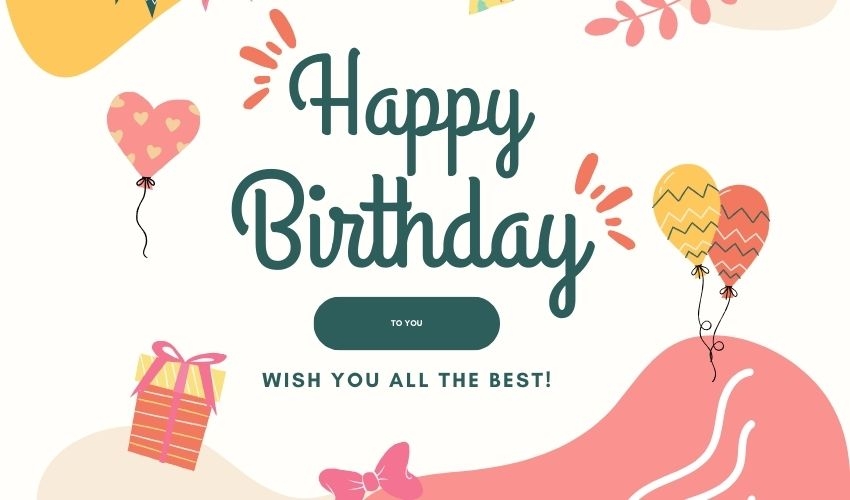
Với các nét vẽ cong nhẹ nhàng cùng các đường nét thanh mảnh, Grand Hotel là font chữ Happy Birthday đẹp mang đến cảm giác tinh tế cho người nhìn. Ngoài việc sử dụng để trang trí trong tiệc sinh nhật, font chữ Gramd Hotel còn được ứng dụng cho nhiều mục đích khác nhau như thiết kế thiệp mời, thiết kế logo, bao bì và website.
4. Font chữ Amsterdam One
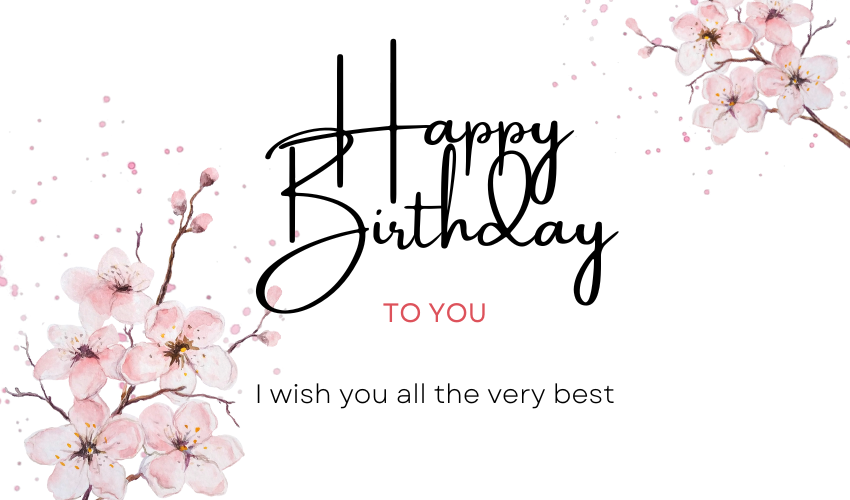
Amsterdam One là font chữ San-Serif đẹp, nổi bật với phong cách hiện đại, sang trọng và đậm chất nghệ thuật. Font chữ có nét cong nhẹ nhàng và các chi tiết tối giản giúp bạn tạo nên các văn bản cuốn hút và độc đáo. Font chữ có phiên bản Regular và Italic để người dùng lựa chọn phù hợp với ấn phẩm thiết kế.
5. Font chữ Halimum
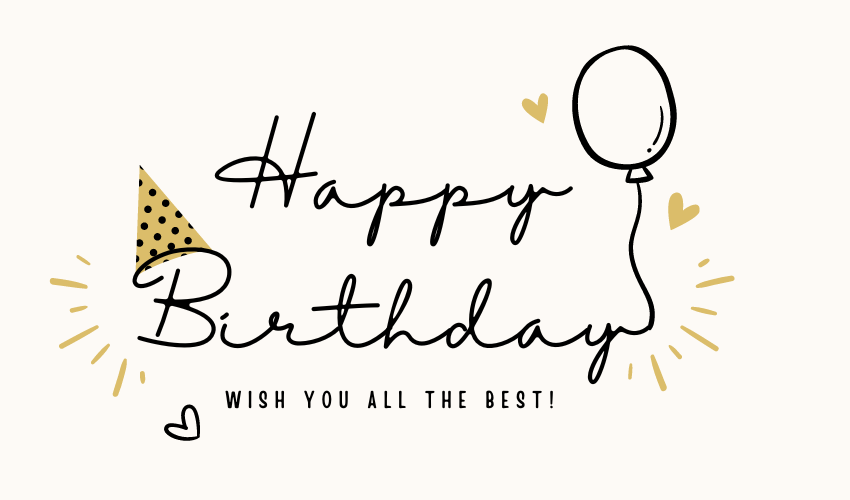
Halimum là font chữ cách điệu rất phù hợp trong thiết kế banner, thiệp mời, sản phẩm thời trang, đặc biệt là trong trang trí tiệc sinh nhật. Font chữ mang đến sự cân bằng giữa các nét thanh mảnh, nhẹ nhàng và liền mạch tạo cảm giác trẻ trung, thể hiện tính thẩm mỹ cao.
6. Font chữ More Sugar
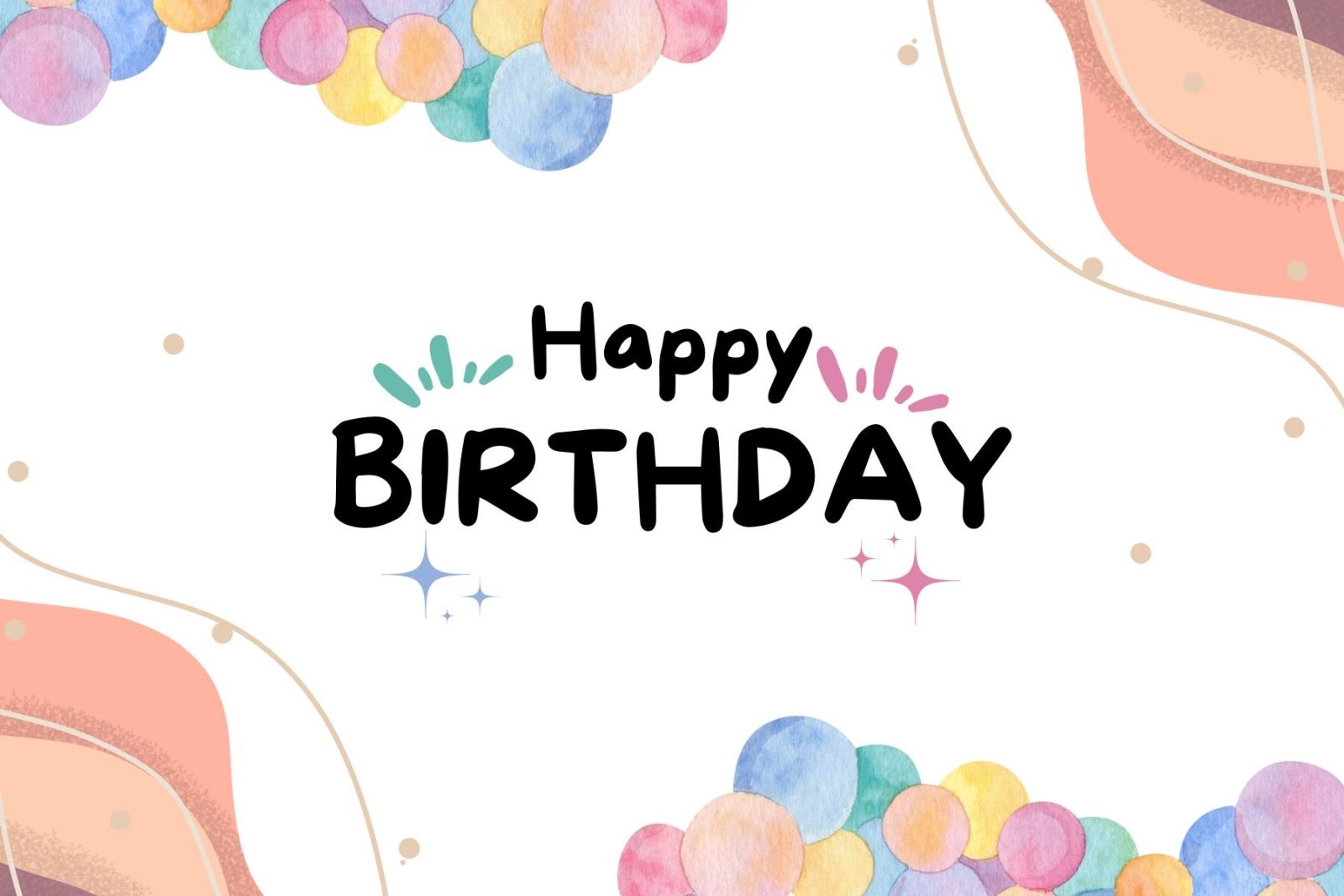
More Sugar là font chữ viết tay kết hợp giữa sự sáng tạo và tối giản. Font chữ có nét viết tự nhiên, đường nét uyển chuyển mềm mại tạo ấn tượng thị giác cho người nhìn. Bộ font More Sugar bao gồm các biến thể khác nhau như Regular, Thin và Extras giúp bạn tạo nên nhiều văn bản, hình ảnh độc lạ. Font phù hợp với việc thiết kế poster, banner, logo, thiệp mời, thiệp chúc mừng, sản phẩm thời trang,...
7. Font chữ Brasika
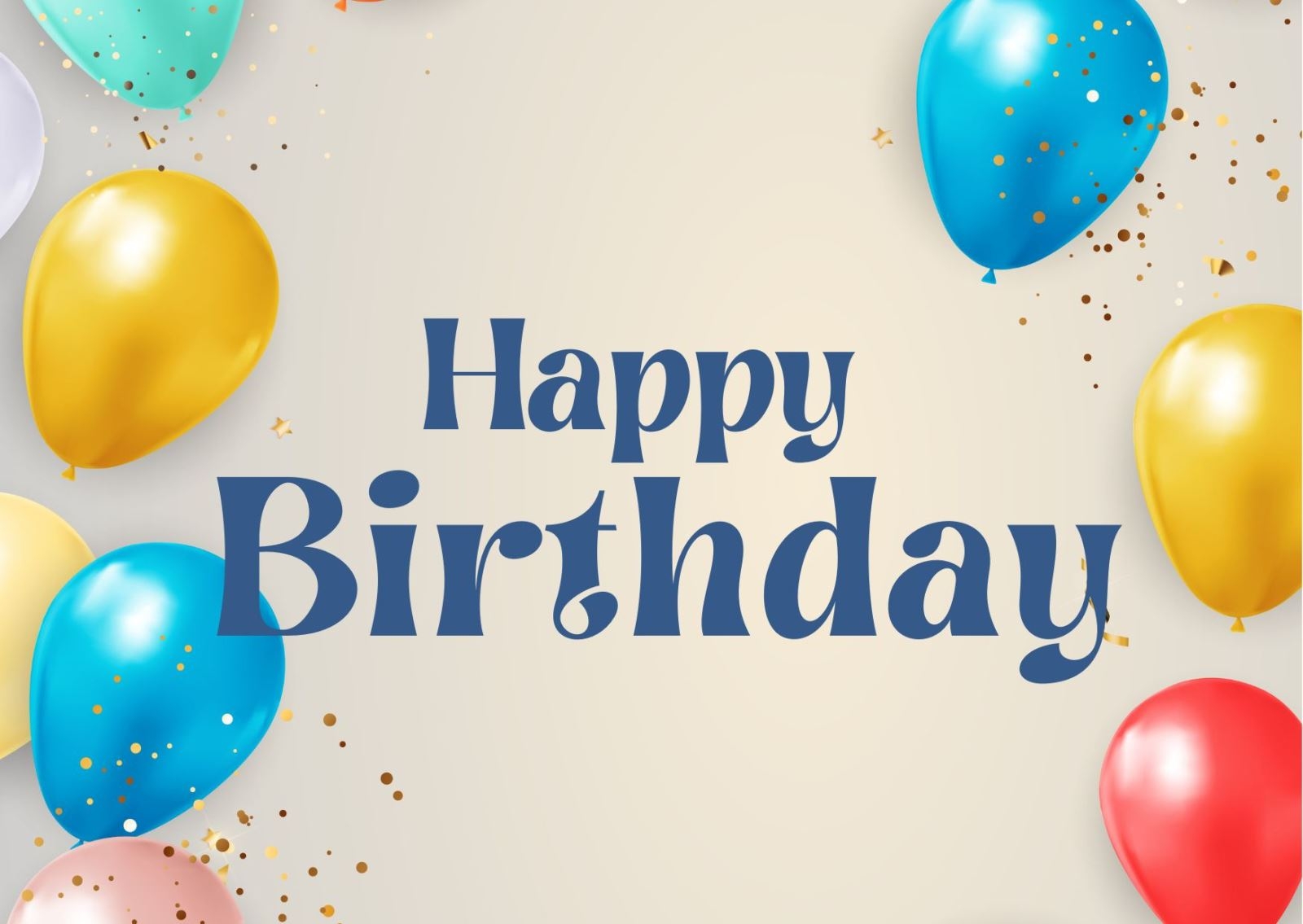
Brasika là font chữ Happy Birthday độc đáo với phong cách vui nhộn, các đường nét dày đậm, xoắn ốc mềm mại làm cho dòng chữ thú vị hơn. Font chữ Brasika gồm cả chữ hoa và chữ thường giúp bạn tạo nên các ký tự, văn bản đẹp mắt, cân đối. Ngoài việc sử dụng để trang trí trong tiệc sinh nhật, font chữ Brasika còn có thể ứng dụng trong nhiều trường hợp khác nhau như thiết kế logo, thiệp mời, bao bì hay thiết kế trang web. Để dùng font chữ này, bạn có thể tải và cài đặt về máy tính hoặc lên website Canva.com để sử dụng.
8. Font chữ Lazydog
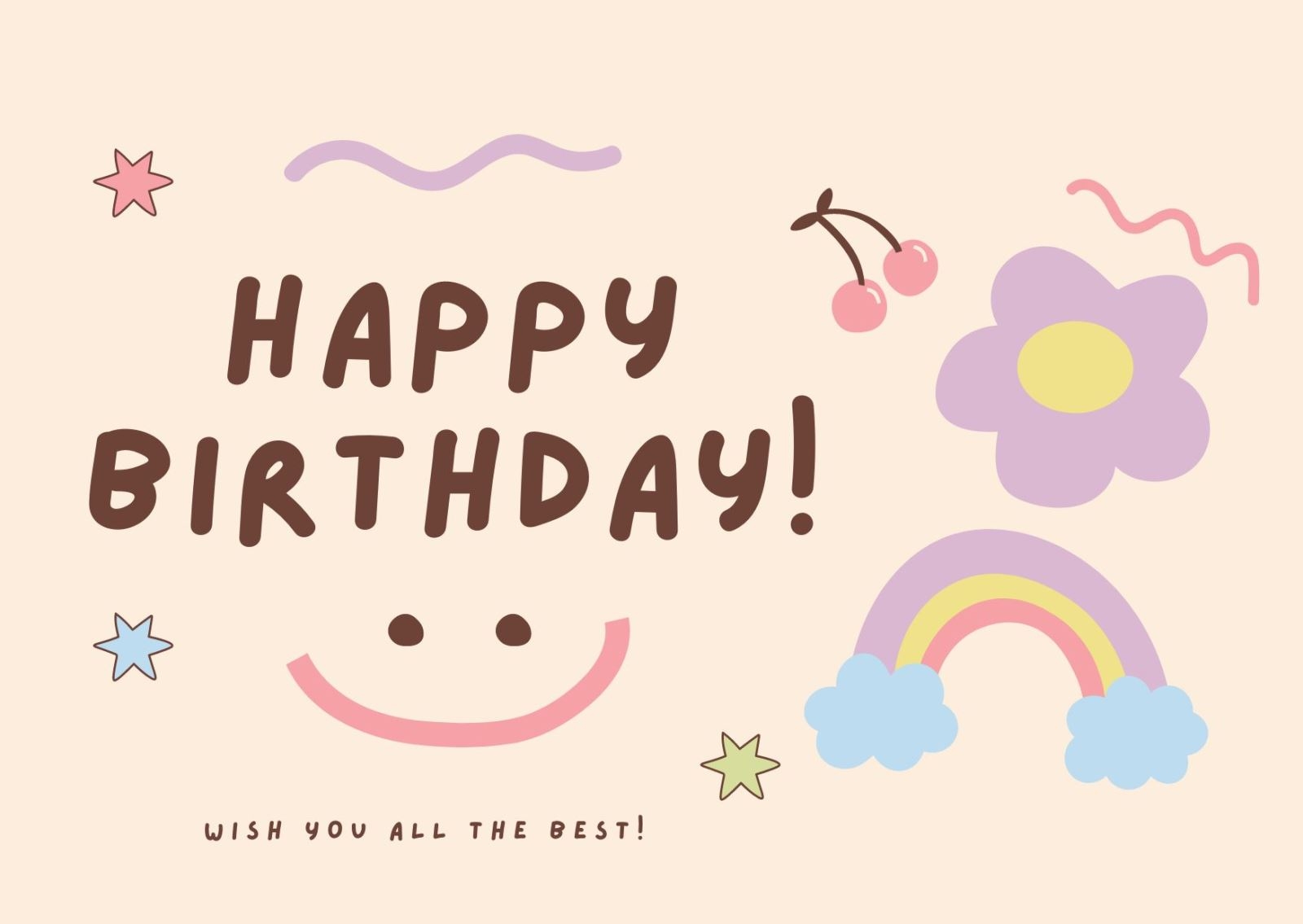
Lazydog là font chữ sáng tạo miễn phí, nổi bật với các đường nét mượt mà, đường cong uyển chuyển và chi tiết trang trí đơn giản, mang đậm phong cách trẻ em. Font chữ này bao gồm đầy đủ bộ ký tự, hỗ trợ các ngôn ngữ khác nhau, trong đó có tiếng Việt.
9. Font chữ Kaushan Script
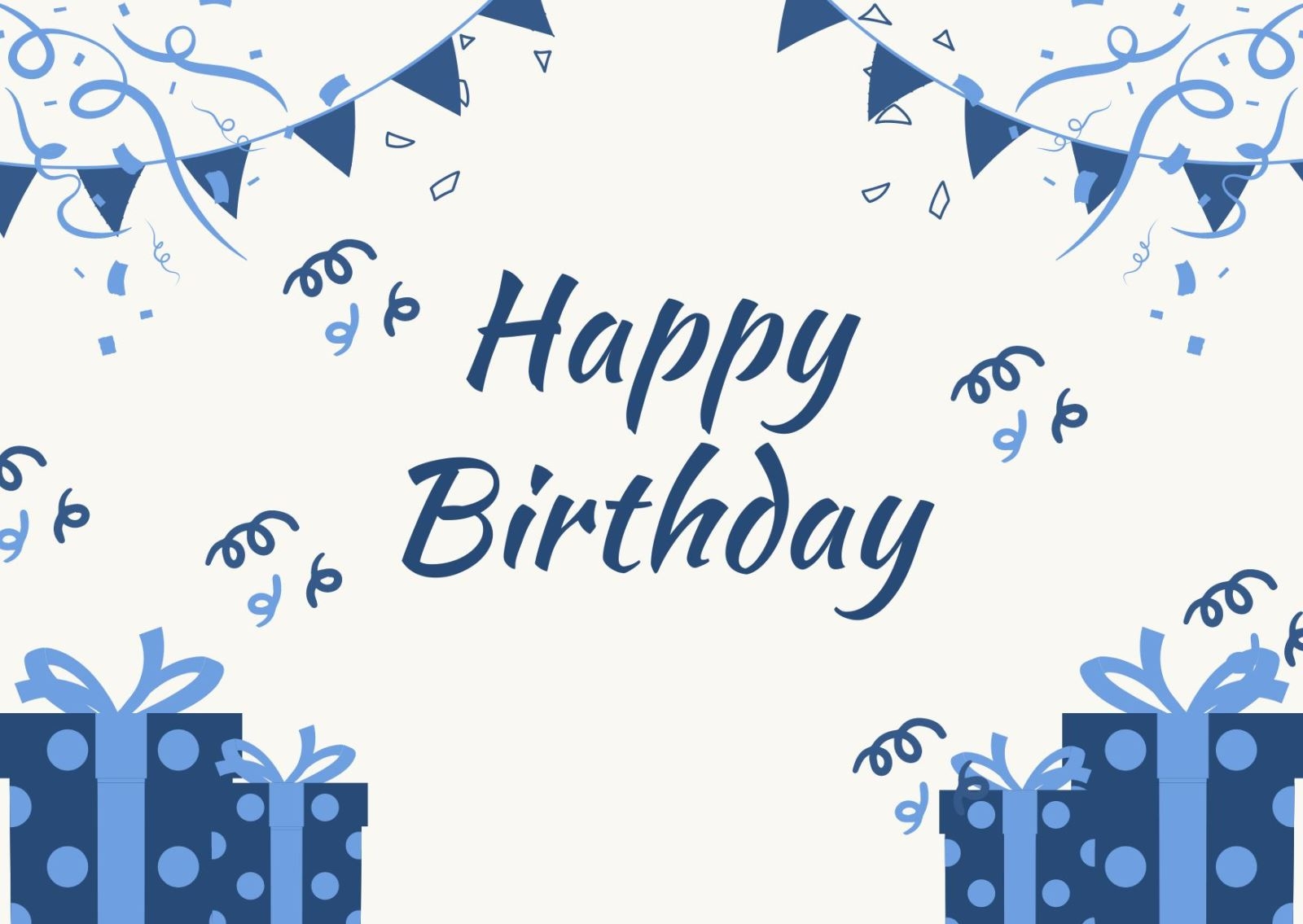
Font chữ Kaushan Script thể hiện được vẻ đẹp hiện đại, thanh lịch. Font có phong cách script mềm mại, tạo cảm giác nhẹ nhàng, phù hợp với các thiết kế mang tính thẩm mỹ cao. Bạn có thể sử dụng font chữ này để tạo điểm nhấn trong trang trí tiệc sinh nhật, thiệp mời, thiết kế logo, ấn phẩm truyền thông,...
10. Font chữ Playfair Display
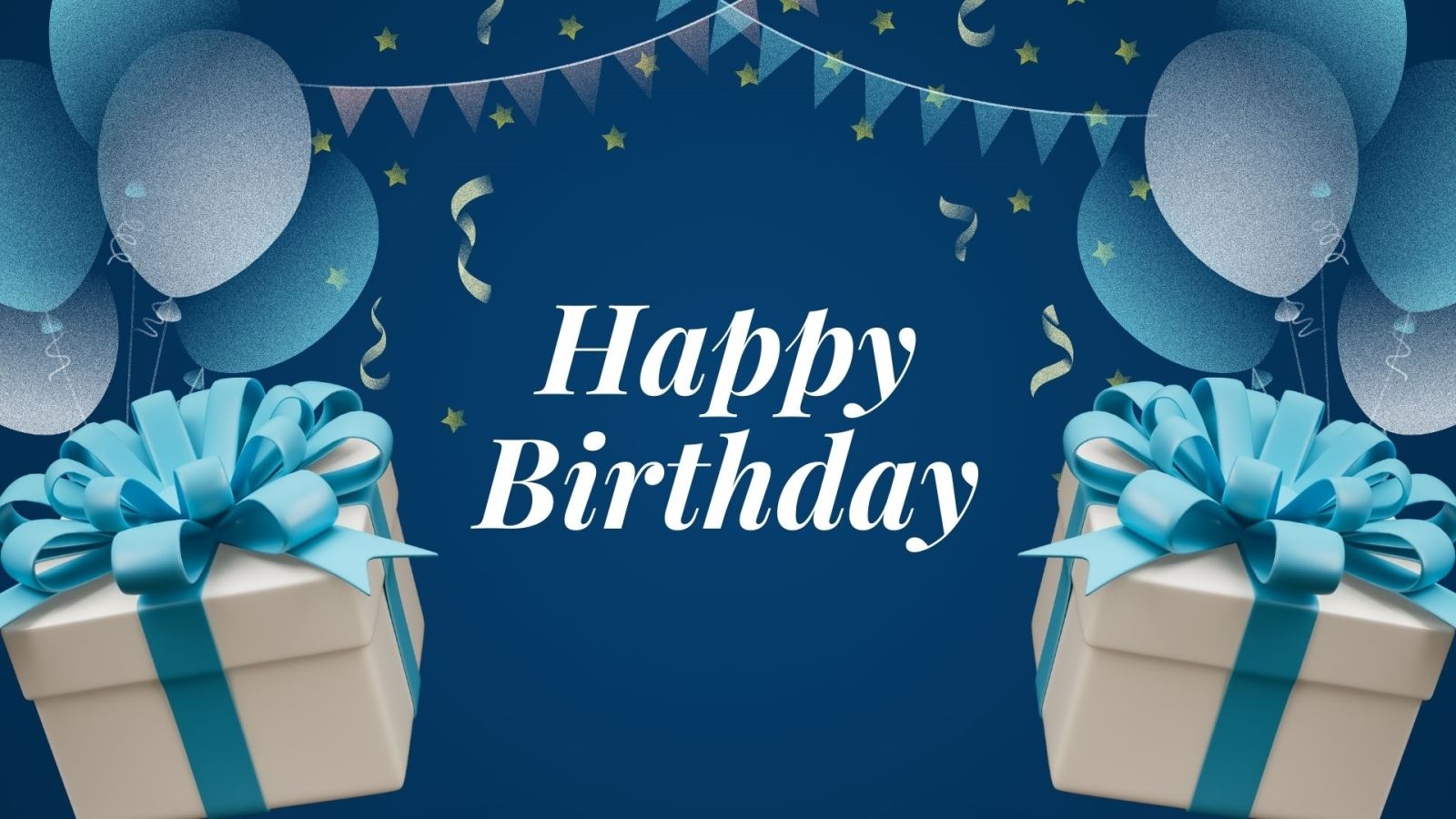
Font chữ Happy Birthday đẹp cuối cùng mà chúng tôi muốn giới thiệu là Playfair Display. Đây là font chữ Serif hiện đại và tinh tế, mamg đến sự cân bằng giữa nét thanh, nét đậm, tạo cảm giác sang trọng. Playfair Display có đa dạng phiên bản, bao gồm Regular, Italic, Bold và Bold Italic giúp bạn lựa chọn phong cách phù hợp với người dùng.
Hướng dẫn viết chữ Happy Birthday đơn giản và tiện dụng
Để tạo nên chữ Happy Birthday đẹp, độc đáo và miễn phí bạn có thể truy cập vào trang web yaytext.com và thực hiện các bước sau:
- Bước 1: Nhập chữ Happy Birthday vào ô Your Text.
- Bước 2: Phía dưới sẽ có các phiên bản Happy Birthday khác nhau để bạn lựa chọn như Bold (serif), Italic (serif), Bold/Italic (serif),... Sau đó, nhấn Copy rồi dán vào trang web, văn bản hay blog mà bạn đang điều chỉnh.
Kết luận